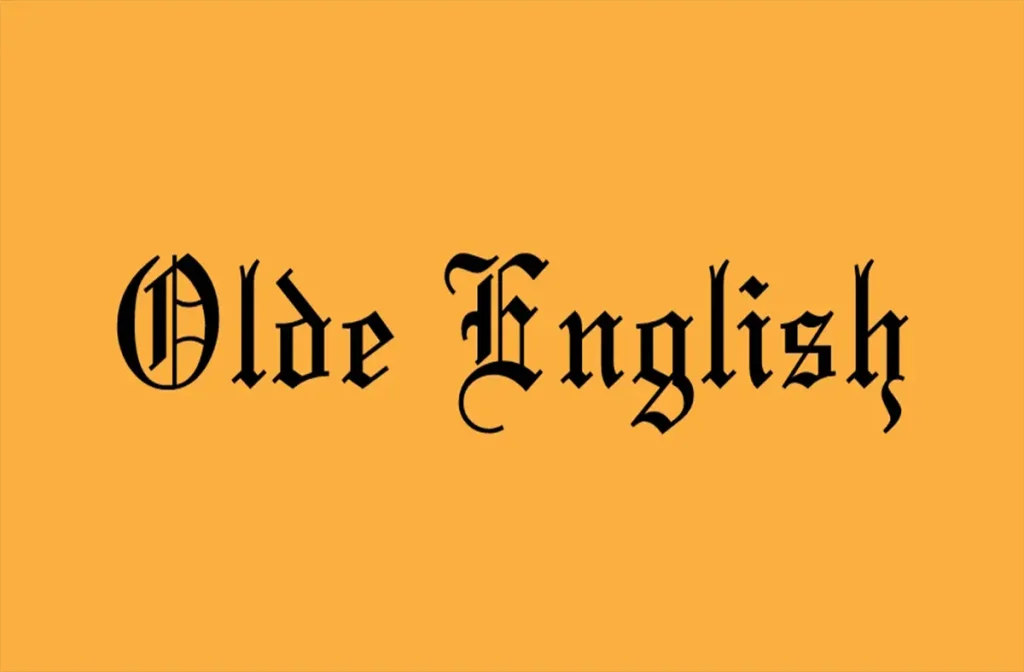
Old English Font Free
Phân loại: Cổ điển
Kiểu chữ: Serif
Old English Font là một phông chữ mang phong cách cổ điển, lấy cảm hứng từ các chữ viết thời Trung Cổ. Font này thuộc bộ font chữ thư pháp, với các đường nét phức tạp, góc cạnh và dày, tạo nên vẻ trang trọng và uy nghiêm. Old English Font thường được sử dụng trong các thiết kế mang tính lịch sử, nghệ thuật hoặc để tạo điểm nhấn cho các tiêu đề, logo, hoặc lời mời đặc biệt. Với tính thẩm mỹ độc đáo và đậm chất truyền thống, phông chữ này giúp tái hiện không khí cổ kính và sang trọng trong các tác phẩm thiết kế.